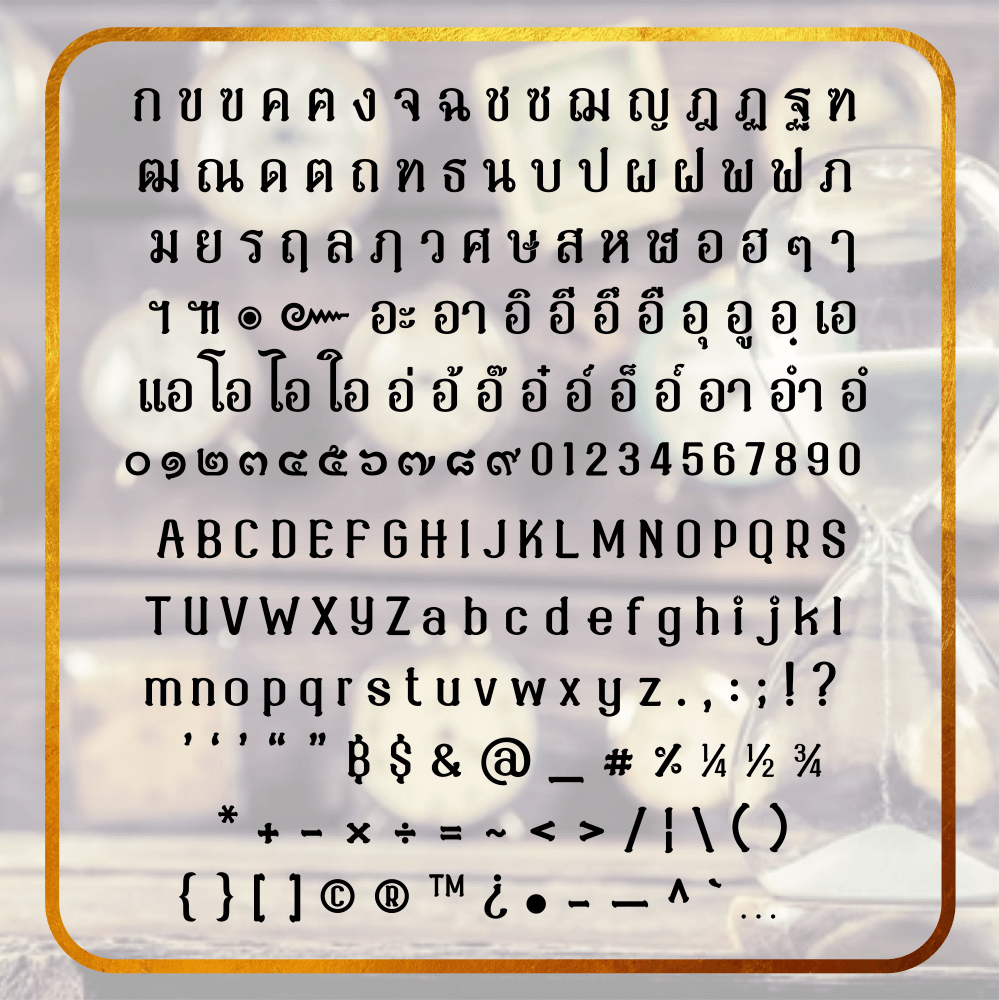
j.devilfont@ruam samai (ร่วมสมัย)
ผลงานชิ้นที่ 3 ฟอนต์ร่วมสมัย ลักษณะตัวอักษรต้องการความร่วมสมัย เรียบหรู บ่งบอกถึงความเป็นไทย รูปแบบฟอนต์สามารถเปลี่ยนขาได้ถึง 4 แบบ แล้วแต่ความชอบของผู้นำไปใช้งานครับ
ลูกเล่นยังเป็นเช่นเดิมตามคอนเซปต์ Devilfont
– เวลาพิมพ์จะไม่มีปัญหาเรื่องการทับซ้อนของตัวอักษร สระ วรรณยุกต์
– ใช้ mark เข้ามาจัดการแก้ไขปัญหาเวลาต้องการปรับระยะห่างของตัวอักษรมากขึ้น แต่สระจะอยู่ตำแหน่งเดิมไม่ขยับตาม
– ใช้ kerning ในการจัดช่องไฟ ระยะตัวอักษร + ตัวอักษรพิเศษ